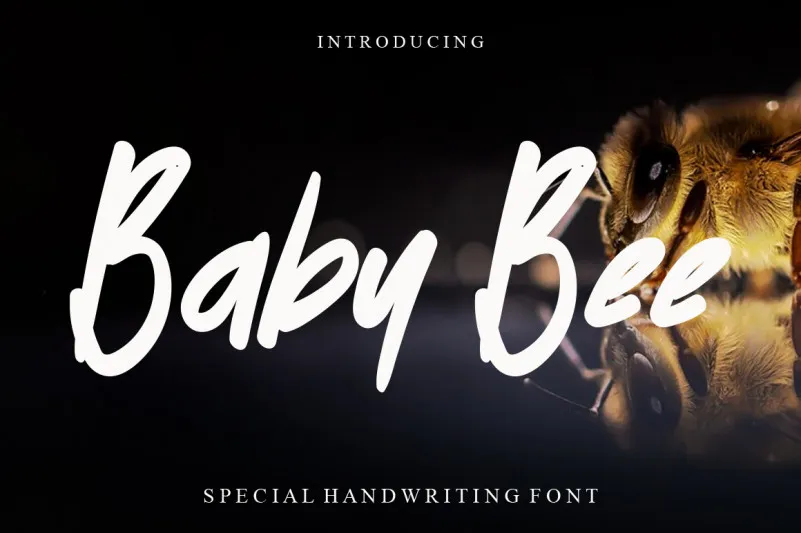
Baby Bee Font
A fonte “Baby Bee Font” é uma elegante fonte escrita a mão círculo que se destaca por seu charme genuíno e delicado estilo cursivo. Essa fonte suave e fofa será perfeita para adicionar um toque alegre e romântico aos seus projetos, tornando-os ainda mais encantadores e atraentes. Ideal para aplicar em materiais de decoração ou design gráfico que buscam um ar delicado e retrô. Seja para cartazes, postais ou até mesmo designs digitais, essa fonte trará uma atmosfera única e fresca ao seu trabalho. Seja você designer web, gráfico ou artista digital, a “Baby Bee Font” é uma escolha perfeita que certamente deixará sua marca de forma autêntica e divertida.